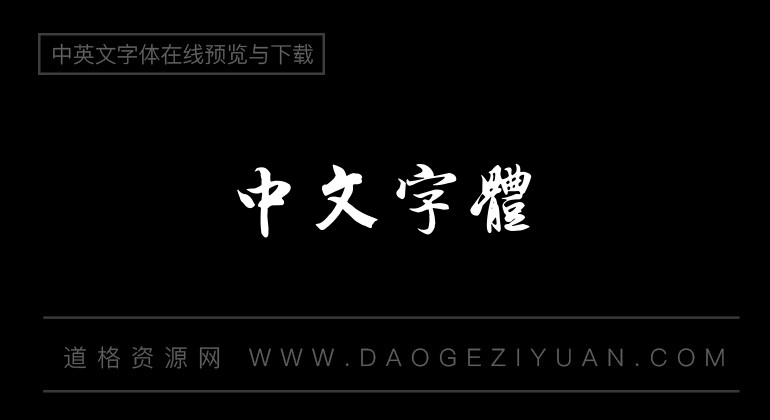
兰亭集序书法字体
兰亭集序书法字体是一种典雅、文艺、细腻的汉字书法字体,由宋代书法大家王羲之创作,以其细腻的笔画、优美的线条、精致的结构和柔和的韵律,使其成为中国书法史上一项重大的成就,也是中国书法史上最受欢迎的书法字体之一。兰亭集序书法字体的特点是结构简洁、笔画精致、线条优美,这些特点使得它在书法创作中十分受欢迎。
兰亭集序书法字体是一款非常不错的手写艺术字体,具有很好的视觉感,适合于文化类的宣传设计、商业类品牌的广告和产品包装设计以及个性化文字排版等较多场景。